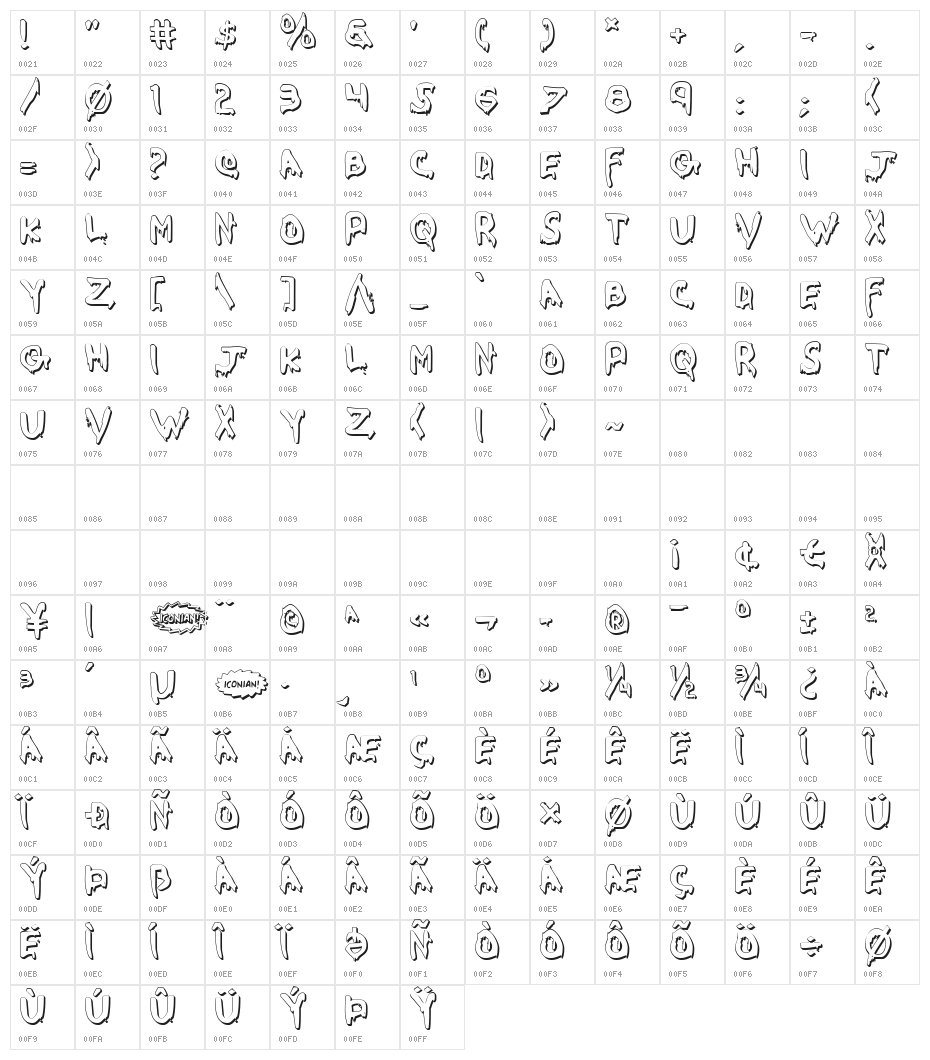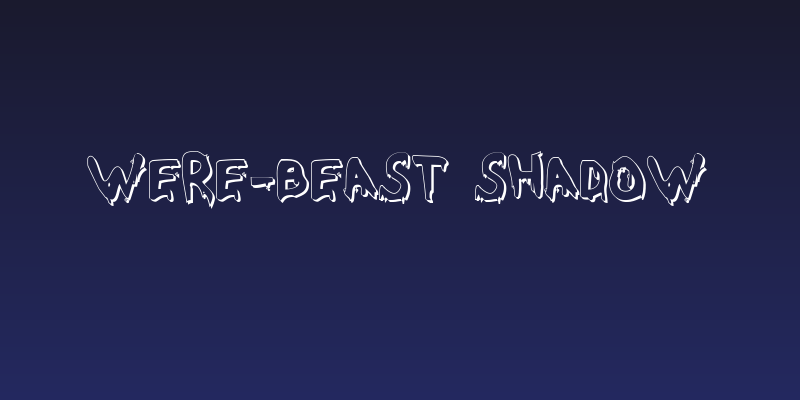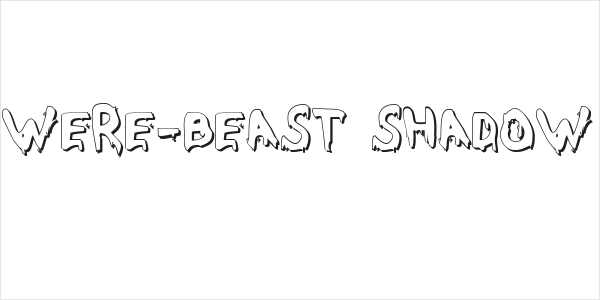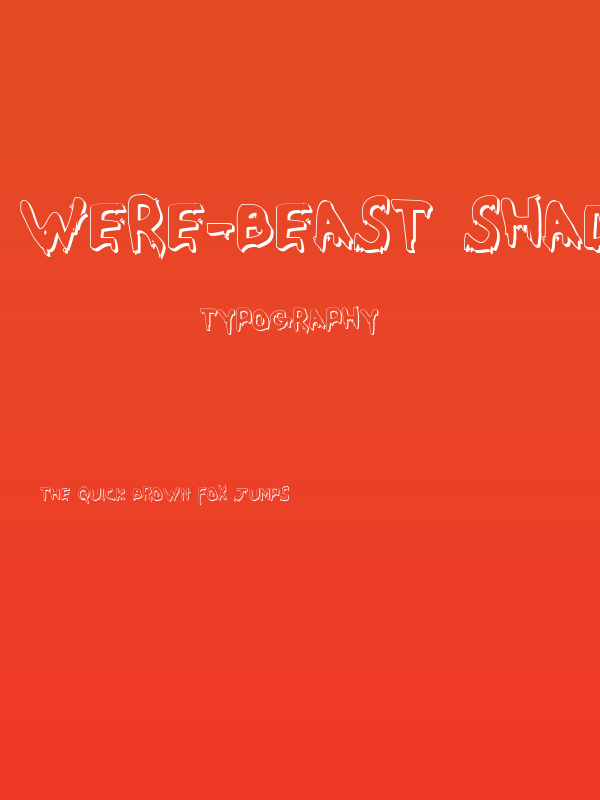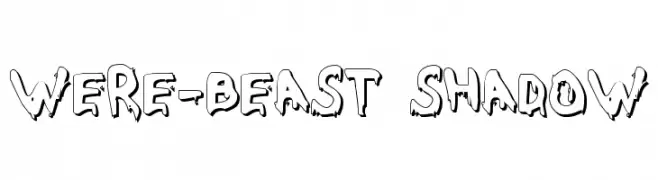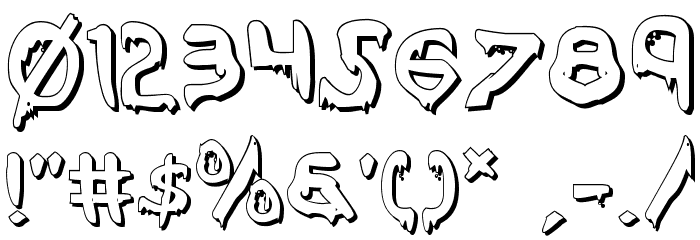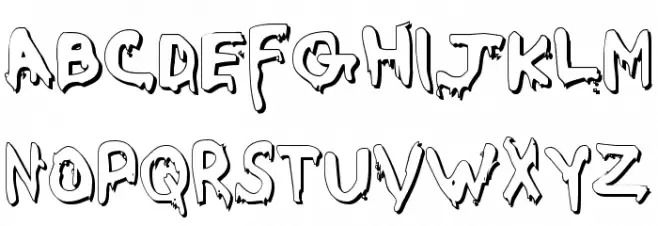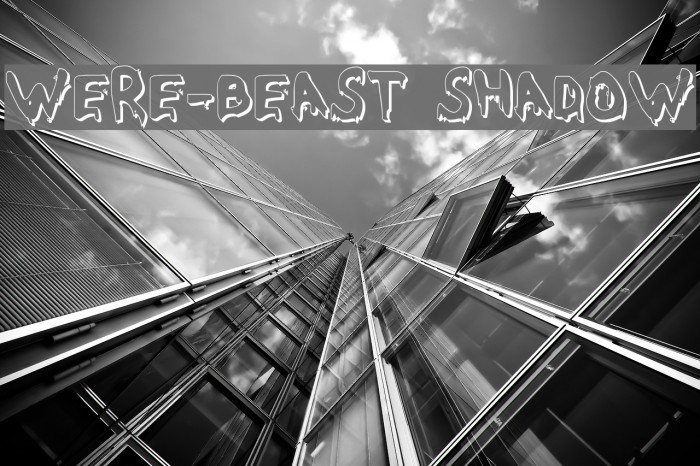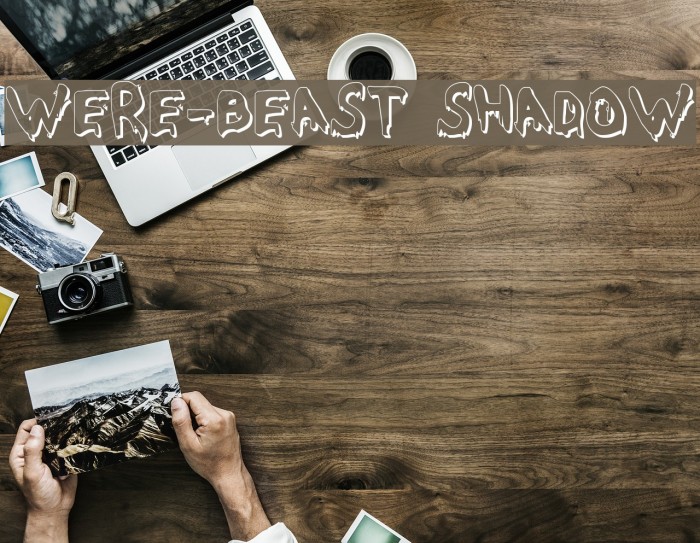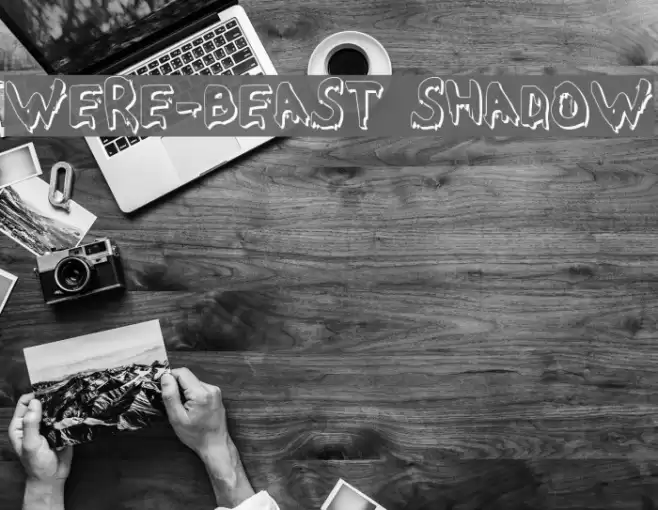
Were-Beast Shadow Font
| おすすめプロジェクト | Ideal for Halloween-themed designs, horror movie posters, haunted house flyers, and any project requiring a creepy, atmospheric touch. |